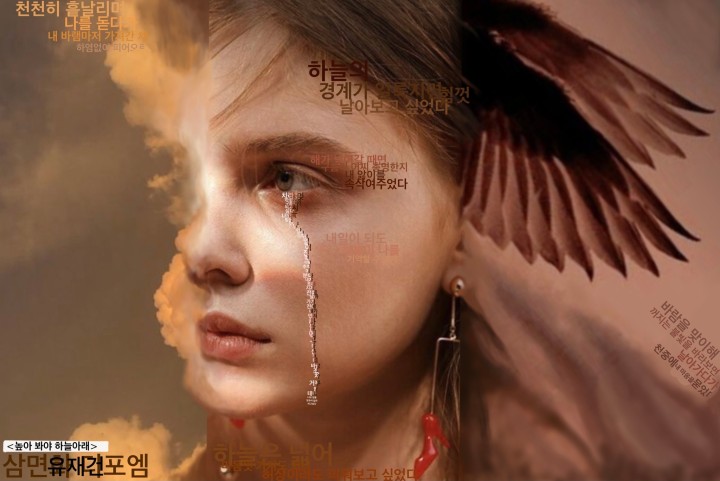
<높아 봐야 하늘 아래>, 유재건
사진 세 장을 이어붙인 삼면화 형식의 <높아 봐야 하늘 아래>는, 보자마자 각각 다른 세 장이 연결돼 있다는 사실을 깨닫기 어렵게 만들어졌다. 중간중간 배치된 텍스트 또한 그렇다. 왼쪽의 텍스트는 처음 봤을 때 그저 구름으로만 보일 뿐이며, 가운데 이미지 상단의 텍스트는 머리카락, 중간과 하단의 텍스트는 눈매와 눈물, 오른쪽 이미지의 텍스트는 바람을 표현한 선 같다. 이 요소들 사이에서도 시선을 가로채는 이목구비, 색상을 맞춘 구름과 날개는 ‘자유를 갈망하는 인간’을 그리고자 했다는 시의 방향성과도 맞아떨어진다.
독자는 <높아 봐야 하늘 아래>를 마주한 뒤 자연스럽게 이곳저곳으로 시선을 옮겨 하나의 시를 구성하고자 하게 된다. 확대의 기능을 사용해 이미지의 일부가 된 텍스트를 읽고, 그 위치와 방향과 색이 의미하는 바를 추측한다. 다만 이것을 구성하는 순서에 정답은 없다. 그 높은 자유도가 디지털 포엠을 즐기는 방법 중 하나이기도 하다.
모든 문장은 화자의 발화이며 감정의 분출이다. 시의 화자는 하늘에서 자유를 찾고자 한다. ‘하늘의 경계가 얼룩지면 힘껏 날아보고 싶었다’는 화자의 외침은, 결국 눈물을 본뜬 텍스트 안에서 ‘차라리 하늘의 구름이 되고 싶었다’는 말로 마무리된다. ‘하늘’이라는 공간을 계속해서 언급함에도 불구, 오히려 땅을 연상시키는 색이 메인으로 사용된 것도 눈여겨 볼 만하다. 어쩌면 이것이 화자의 세상일지도 모른다.
하지만 그럼에도, 화자의 삶에는 다음 바람이 도착하리라. 그 바람이 아주 자유롭고 강해서, 한 인간을 넓고 높은 하늘에 가닿도록 해 줄지 모를 일이다.
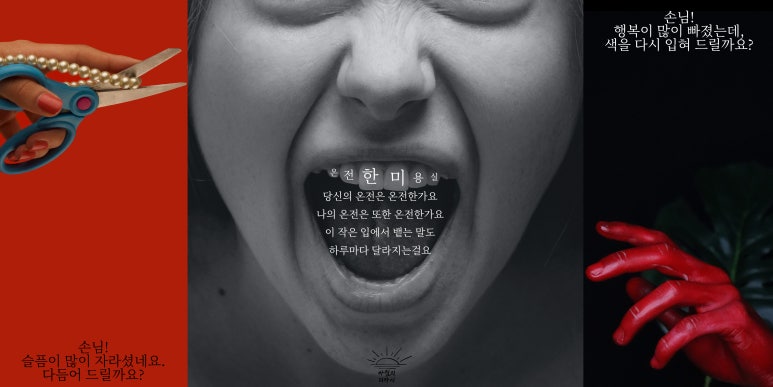
편희주, <온전한 미용실>
삼면화 형식의 <온전한 미용실>은 그 강렬한 이미지로 보는 이를 단숨에 사로잡을 수 있는 작품이다. 커다랗게 입을 벌린 클로즈업 샷과 붉은 손, 채도 높은 매니큐어와 가위 등 어디 하나 긴장을 늦출 수 있는 곳이 없다. 텍스트는 벌린 입 안 치아의 크기에 맞추어 배열되었지만, 어딘가 불규칙하고 아슬아슬한 느낌을 주기도 한다.
작가는 <온전한 미용실>이 제목 그대로 인간의 온전함을 이야기하는 작품이라고 말한다. 인간은 시간이 지남에 따라 변질되기 마련인데, 몇 년이 훌쩍 흐른 뒤에도 어째서 인간은 스스로의 온전함을 맹신하는가.
일종의 ‘테세우스의 배’와 같은 질문을, 우리는 검고 빨간 작품 앞에 서성이며 오래 고민하게 된다. 영웅 테세우스가 타고 돌아온 배의 판자를 갈고 또 갈으면 어느 순간 테세우스의 손길이 닿았던 부분은 하나도 존재하지 않게 될 것이다. 우리 내면의 즐거움과 괴로움을 오래 바라보다 보면 그것은 어느날 아주 다른 형태가 되어 있을 것이다. 그때도 그 배를 테세우스의 배라고, 그 마음을 나의 마음이라고 부를 수 있을까.
자라버린 슬픔과 색이 빠진 행복, 닳고 비틀리는 삶에서 우린 몇 번이나 미용실을 방문해야 할까.
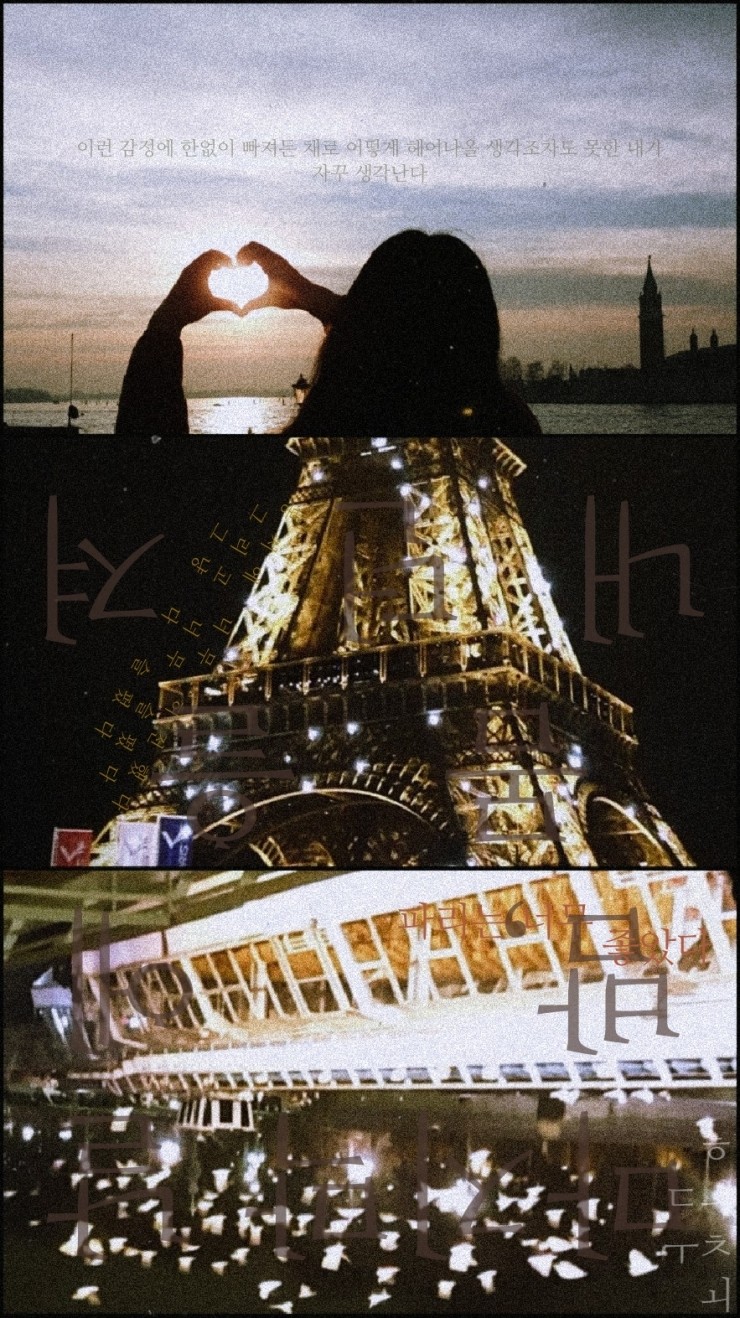
최두희, <마지막 날 밤, 센강에 몸을 내던져 버리고 싶었다>
<마지막 날 밤, 센강에 몸을 내던져 버리고 싶었다>는 온통 프랑스 파리다. 에펠탑의 모양을 한 형상과 센강, 여행 중 촬영되었을 파리 어드메의 장면들이 가득하게 담겨 있다. 그 환한 불빛들을 따라가다 보면, 낯선 이국의 인파 속에서 느끼게 되는 희미한 향수와 충동들이 담긴 텍스트를 발견하게 된다.
작품 속 텍스트들은 크기가 제각각이고 종종 뒤집혀 있기도 하다. 확대해서 살피지 않으면 눈에 잘 띄지 않을 색으로 이미지 속에 숨겨진 글자도 있다. 사람들은 작품을 감상하며 고개를 돌리고 화면을 전환하며 조금 더 능동적인 읽기를 하게 된다. 결론적으로 그렇게 최종적 문장 하나에 다다르게 되고, ‘이런 감정에 한없이 빠져든 채로’ 헤어나올 수 없었던 내가 과거를 회상하는 중이라는 사실을 알 수가 있다.
<마지막 날 밤, 센강에 몸을 내던져 버리고 싶었다>는 파리의 에펠탑과 센강을 중심으로 조명하고 있지만, 우리는 마지막 날의 공항에서 비행기를 기다리는 화자의 모습을 상상해 볼 수 있을 듯도 하다. 이것이 시의 이미지라는 것이 아닐까.
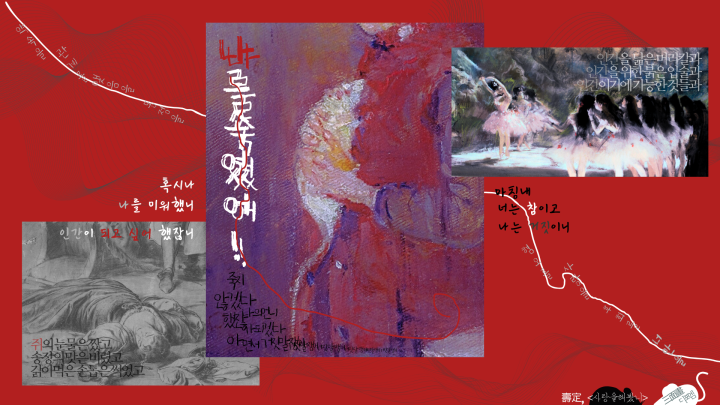
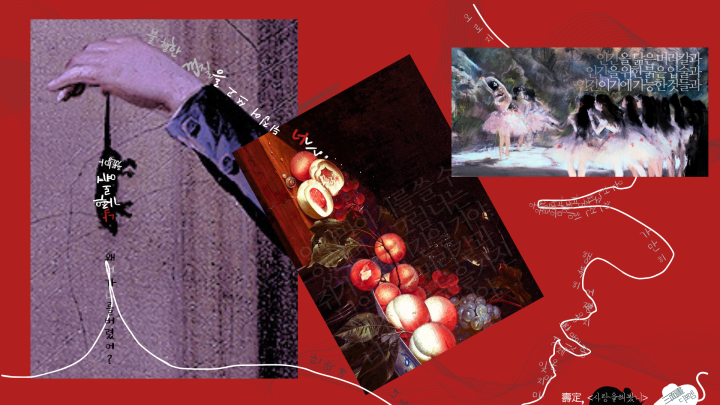
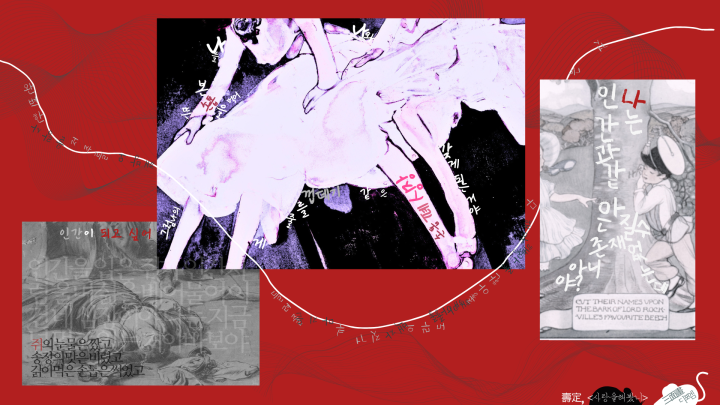
이수정, <사랑을 해봤니>
깎은 손톱을 아무 곳에나 버리지 마라. 쥐가 그것을 오랫동안 주워먹고 주인으로 둔갑하니까. 한 번은 들어본 적이 있을 익숙한 이야기다. <사랑을 해봤니>는 그러한 쥐 둔갑 설화를 바탕으로 만들어졌다. 이미지를 자유롭게 타고 오르는 과감한 텍스트 배치와 강렬한 색채가 눈에 띈다.
시의 형식 또한 평범하지 않다. <사랑을 해봤니>는 삼면화의 형식을 유지하되 사진을 클릭하면 각각 다른 효과음과 함께 장면이 전환된다. 아이의 웃음소리나 유리가 깨지는 소리 등의 사운드는 우리로 하여금 화자의 이야기 속에 완벽히 들어와 있다는 느낌을 준다. 그 이야기에서 우리는 ‘언니’라는 단어를 찾을 수가 있다. 결국 <사랑을 해봤니>는 쥐의 이야기이자 인간의 이야기이자 자매의 이야기가 되는 것이다.
작가는 이 작품을 소개하며 ‘남겨진 자의 설움’이라는 말을 썼다. 그 감정선을 따라 작품을 감상한다면 하얀 선을 따라 작가가 마련한 마지막 페이지에 도착할 수 있을 것이다.
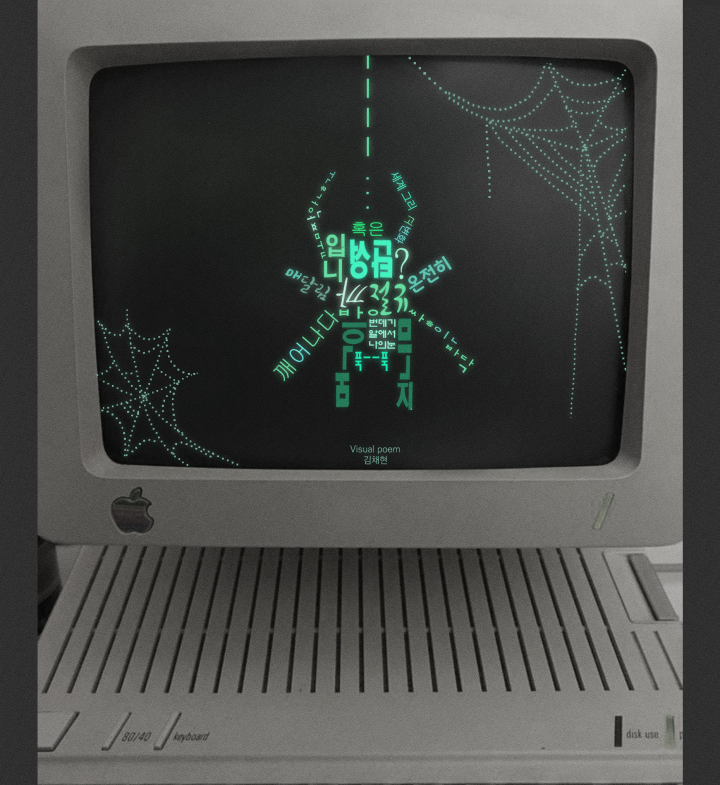
김채현, <거미의 꿈>
거미는 매달린 채 잠들어 세계에 관한 꿈을 꾼다. 거미가 꾸는 꿈은 밝고 환하다. 하지만 길몽이란 무릇 깨어난 이에게 허망함과 혼돈을 제공하기 마련이다. 비주얼 디포엠 <거미의 꿈>은 다양한 폰트와 일정하지 않은 크기, 초록의 계열이되 조금씩 다른 색의 텍스트를 회화적으로 배치해 매달린 거미의 형상을 만들어냈다. 복잡하게 배치된 텍스트는 언뜻 무작위의 단어가 섞여 있는 것처럼 보이지만, 작품을 확대하고 회전하며 읽다 보면 고요하게 세상을 응시하는 거미의 시선을 따라갈 수 있다.
거미의 형상이 나타난 곳이 모니터 안이라는 점도 눈여겨 볼 만하다. 작가는 작품이 ‘불친절한 가독성’을 띠고 있다고 말했다. 거미가 느끼는 현실로부터의 고통을 이해하기 위해서는 앞서 설명했듯 작품을 일반적 텍스트보다 더 오래, 더 신중하게 읽어야만 한다. 하지만 작품이 보여주듯 그 고통은 어디까지나 화면 안 타자의 소유다. 내가 가진 컴퓨터와 휴대폰의 화면을 확대해도 뛰어들어갈 수 없는 그 안의 혼란이야말로 우리가 더 생각해 보아야 할 지점이며, 디지털 포엠만이 표현할 수 있는 어떤 이중의 액자식 구성일 것이다.